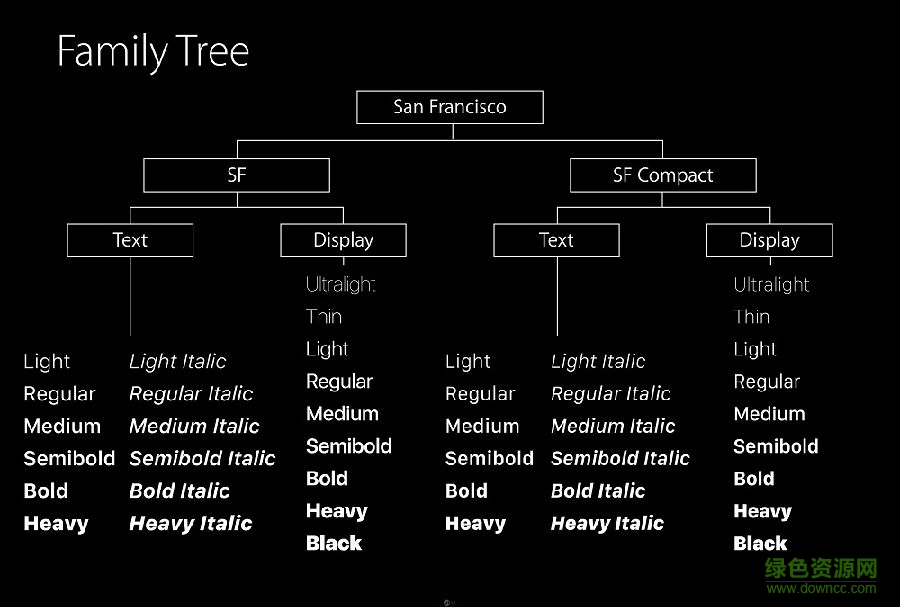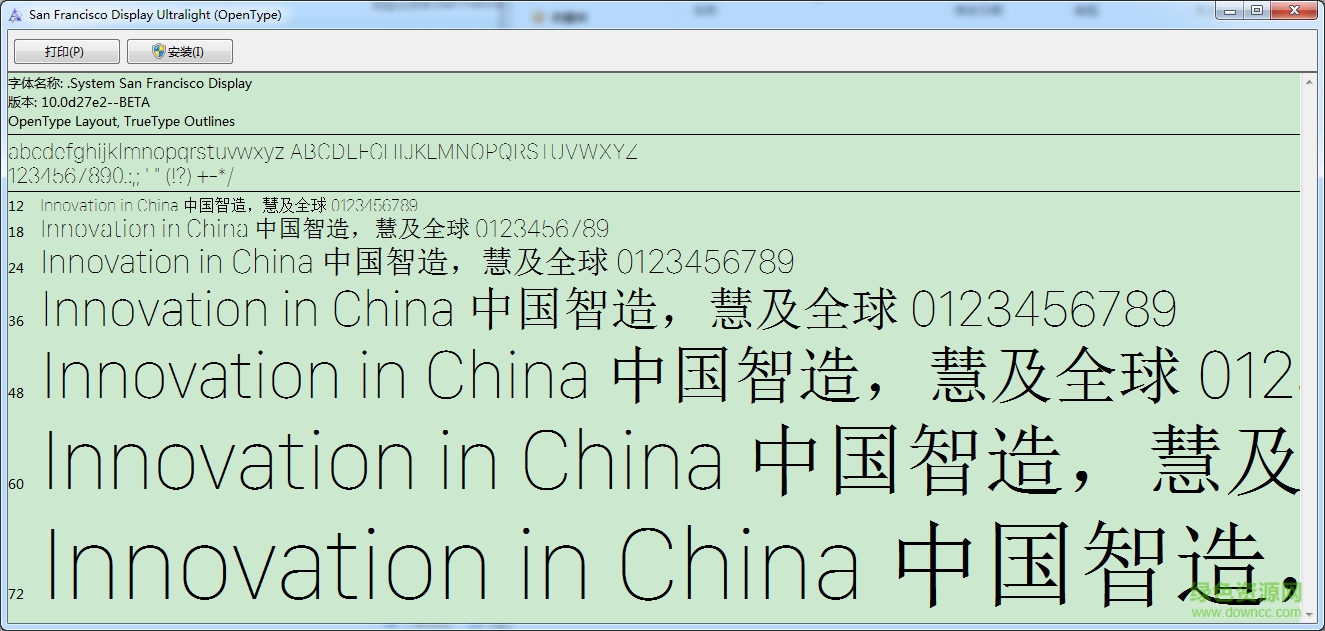
San Francisco是一款蘋果徐婷上的字體,擁有清新簡(jiǎn)潔的造型和外觀,使用起來更顯大方和質(zhì)樸,綠色資源網(wǎng)為大家?guī)磉@款字體的合集,歡迎免費(fèi)下載使用!
San Francisco字族包含了有兩個(gè)字體:SF和SF Compact,各自又分為Text和Display,Text包含6個(gè)字重及對(duì)應(yīng)的斜體,Display包含9個(gè)自重(兩個(gè)細(xì)體和一個(gè)粗體)。
1.San Francisco 是動(dòng)態(tài)字體
作為系統(tǒng)默認(rèn)字體,San Francisco 字體是經(jīng)過動(dòng)態(tài)優(yōu)化的,系統(tǒng)會(huì)隨著字體尺寸的變化而自動(dòng)切換Display/Text兩個(gè)子字體族,通常 20pt 是一個(gè)切換的邊界尺寸。
2.San Francisco 并非單一字體
作為一套系統(tǒng)的字體族,San Francisco 并非是單個(gè)字體,為了保持在不同平臺(tái)上的清晰度,San Francisco字體擁有許多特別的設(shè)計(jì)和功能,如果你仔細(xì)觀察,在iOS和OS X上顯示的San Francisco字體有著微妙的差異。